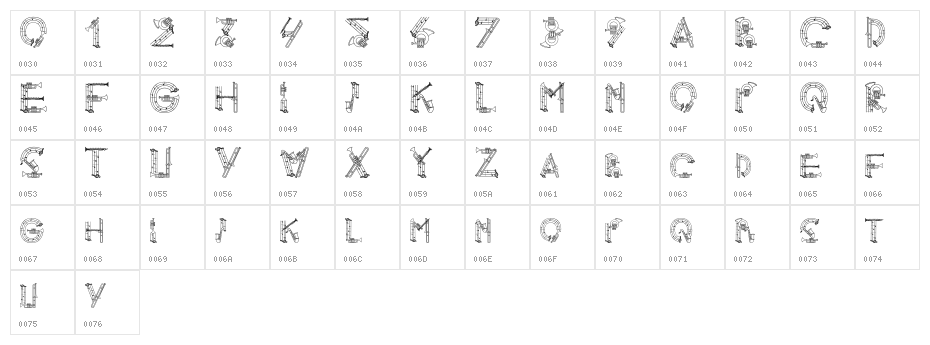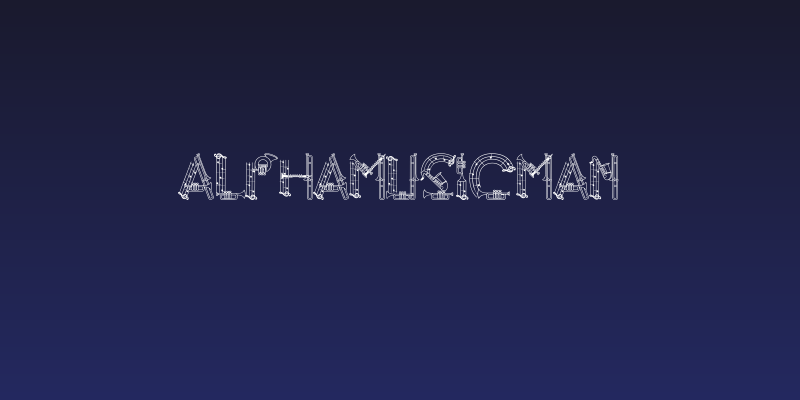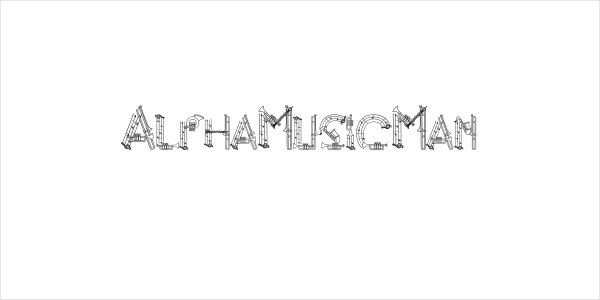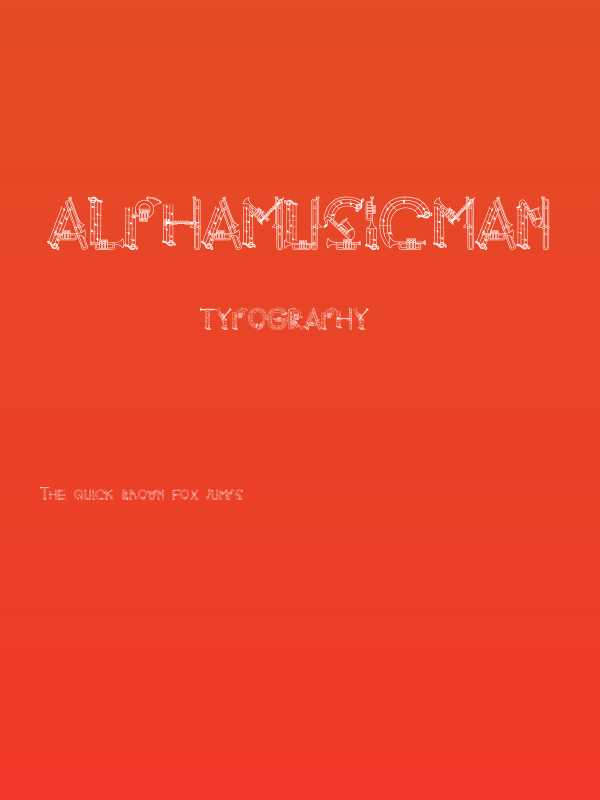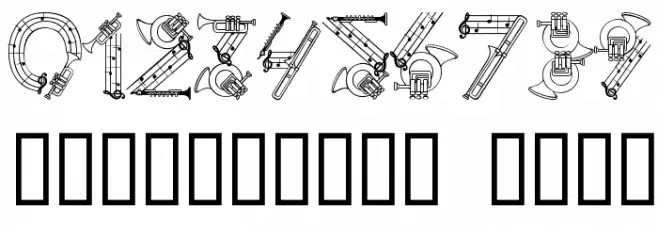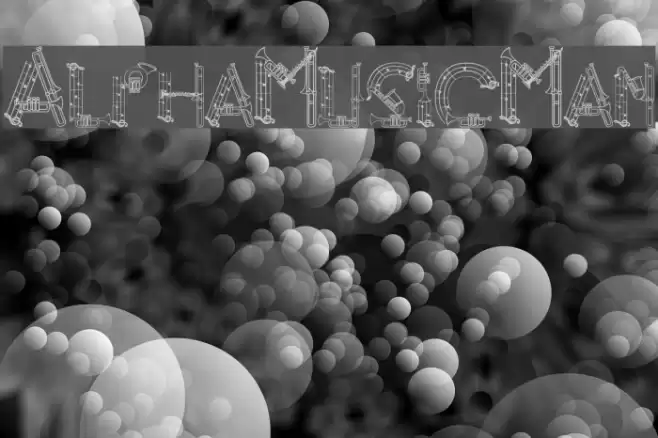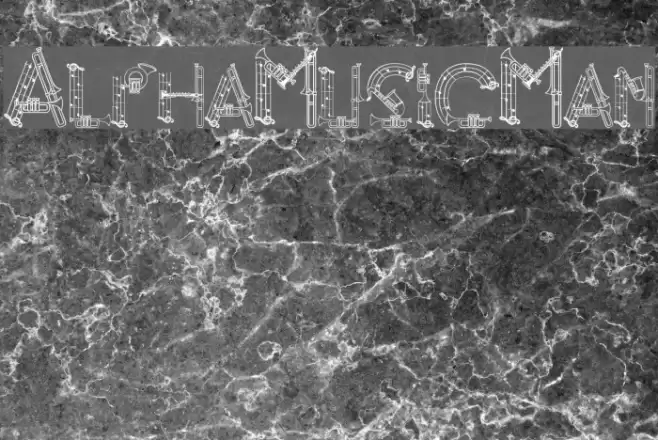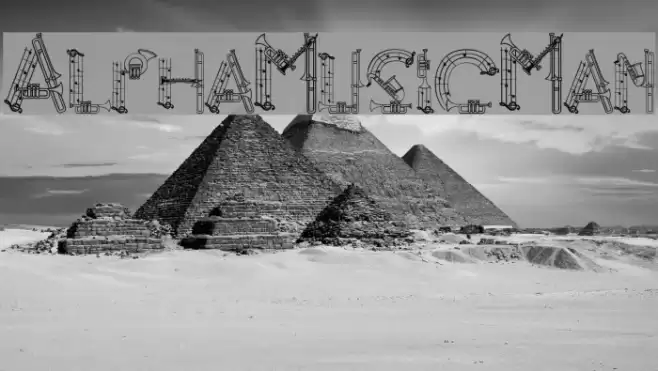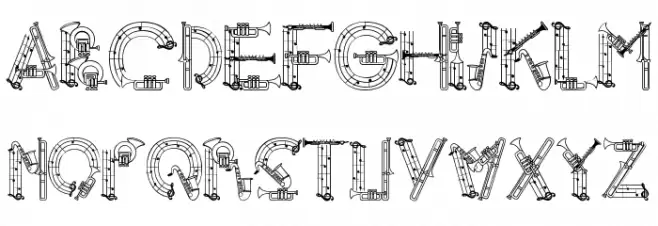
AlphaMusicMan Font
| حالة الاستخدام | Logos, Headlines, Posters |
| مشاريع مقترحة | Ideal for music-themed posters, album covers, event invitations, and educational materials related to music. |